今回は、近未来感やテクノロジー感を演出できる「デジタル風」の日本語フリーフォントをご紹介します。
ピクセル調の文字や、LED風のドット文字、グリッチ感のあるデザインなど、デジタルテイストのフォントは、映像・ゲーム・ガジェット・サイバー系コンテンツにぴったりです。シャープな印象や、ちょっと無機質でデジタルっぽい雰囲気が、世界観をグッと引き締めてくれるフォントばかりです。
今回は、そんなデジタル風なデザインをした日本語フリーフォントをピックアップしました。クールで未来感のあるビジュアルを目指したいときに、ぜひ取り入れてみてください。
デジタル感ある日本語フリーフォントまとめ
以下サンプル画像は、本記事で紹介しているフォントの一部ですが、ピクセル調の文字や、LED風のドット文字、グリッチ感のあるデジタル感を感じるフォントをピックアップしてご紹介します。
こんてにゅー 2P
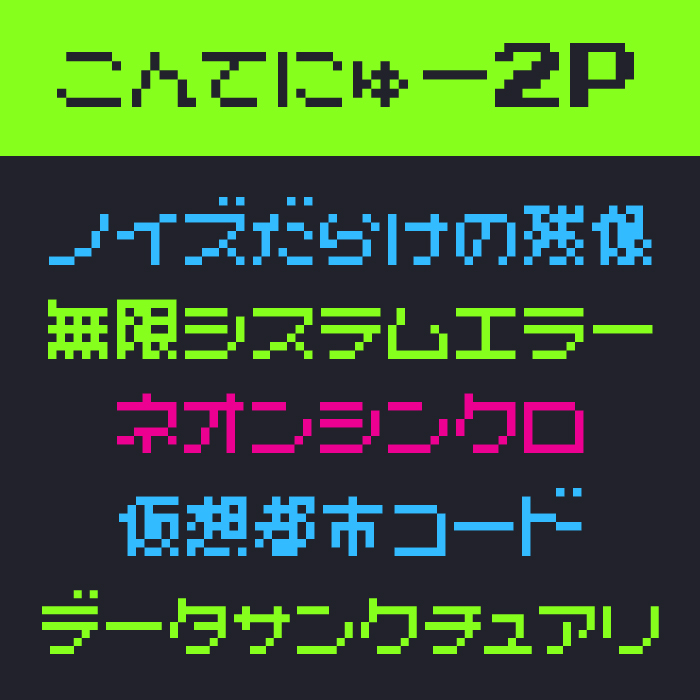
こんてにゅー 2Pフォントは、昔のゲーム画面を思わせるレトロでカクカクしたピクセル感が魅力のフォントです。デジタルノイズやエラーメッセージ風の表現にぴったりで、80〜90年代テイストのデザインにも相性抜群です。
瀞ノグリッチ明朝
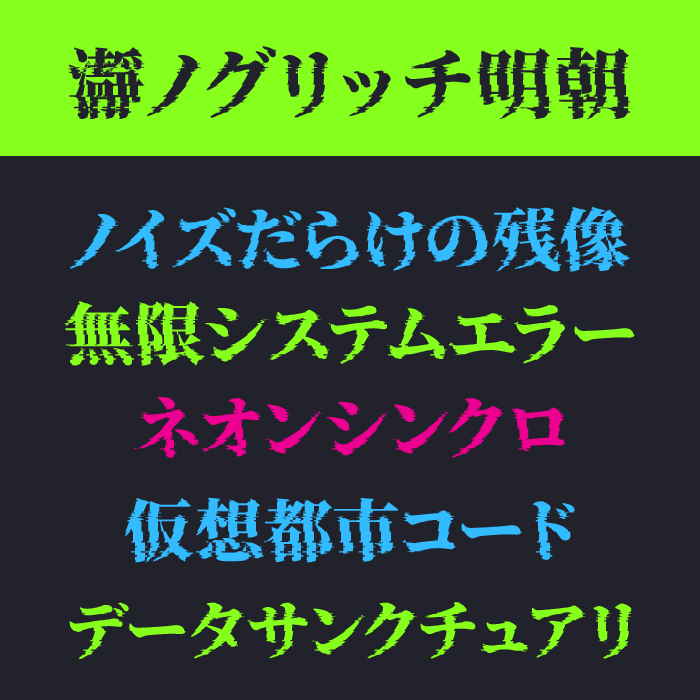
瀞ノグリッチ明朝フォントは、壊れかけた映像のようにザラついた輪郭が特徴の明朝体です。文字のひび割れやゆがみがグリッチ演出とマッチし、ホラー・SF・電脳世界系のタイトルロゴに使いたくなる雰囲気です。
ドット道玄坂12
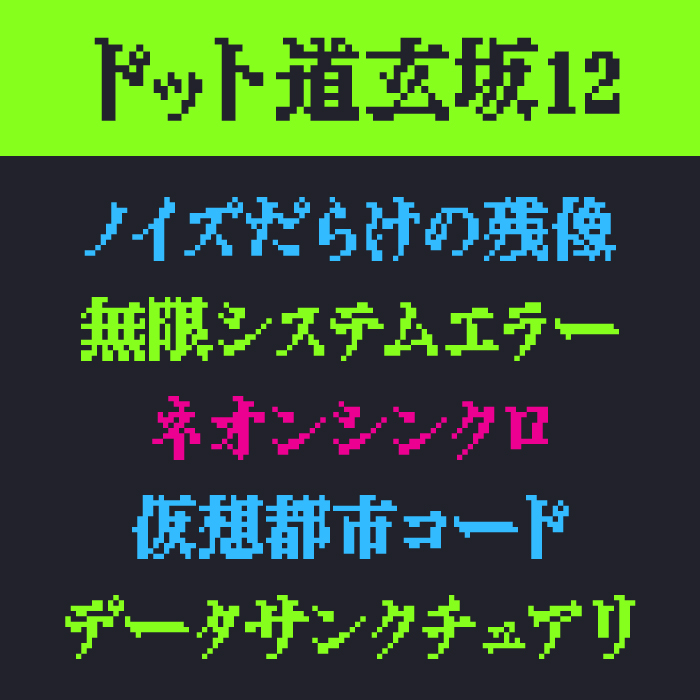
ドット道玄坂12フォントは、ドット感あふれる画素表現で構成されたレトロゲーム風のフォントです。太く安定感のある造形で、ビビッドなネオン配色と合わせることでY2Kやサイバーパンク的世界観がしっかり伝わります。
地方野球場電光掲示板
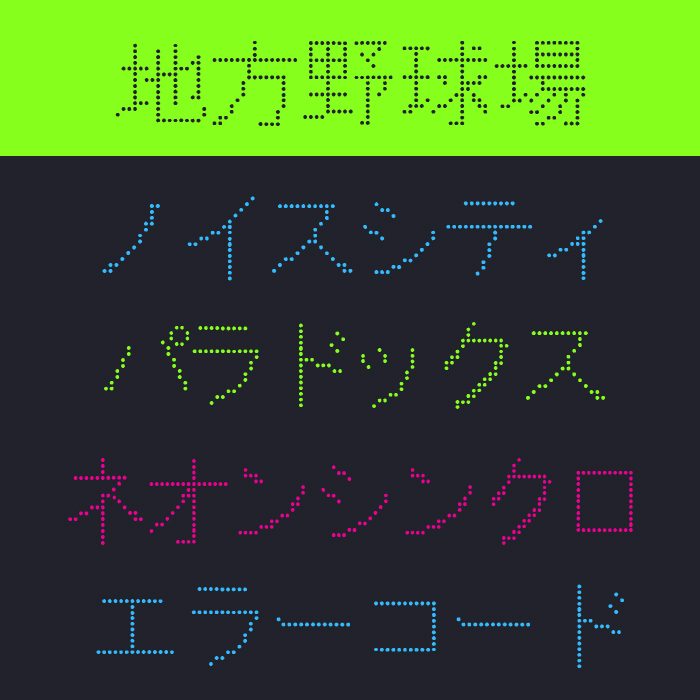
地方野球場フォントは、点線だけで構成されたユニークなディスプレイ書体です。スコアボードや電光掲示のような雰囲気をもち、情報表示やサイバー都市のビジュアル表現にぴったりな存在感を放ちます。
レシートフォント
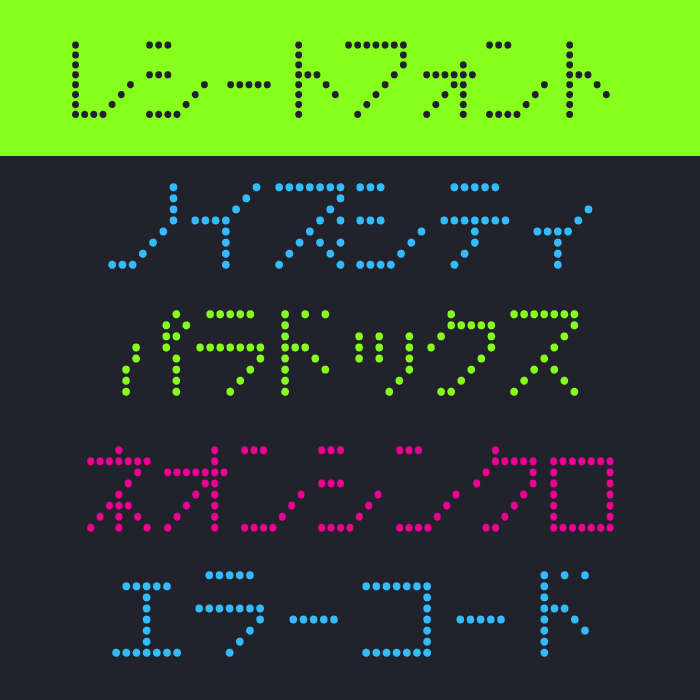
レシートフォントは、実在するレシート印字を模したような細かいドットによる構成がユニークです。古びたレジプリンタやエラー出力などの世界観にハマりやすく、廃墟テックやアンビエント系演出にもおすすめです。
オリエンタル
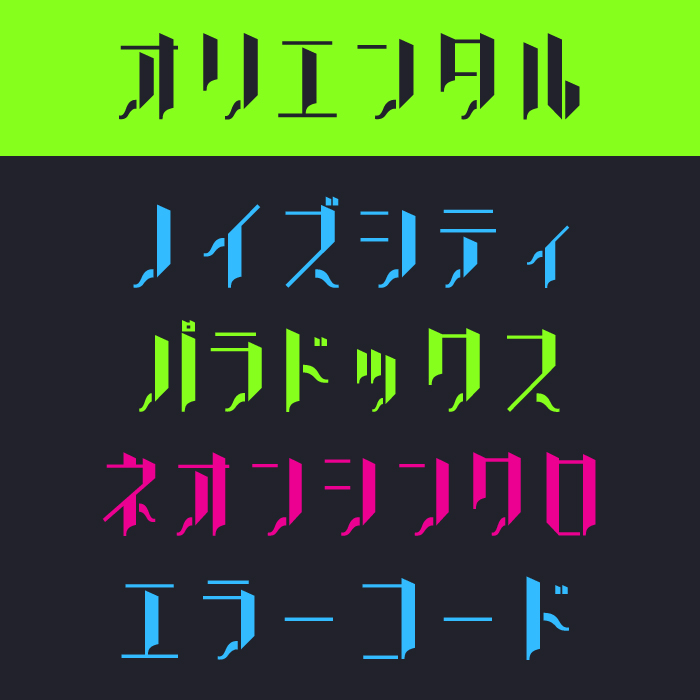
オリエンタルフォントは、漢字の一部が抜け落ちたようなデザインと、角度のあるパーツが特徴の装飾的フォントです。デジタル故障や監視社会、ブロークンな世界観を表現するタイトルやUIに適しています。
JikiTourai
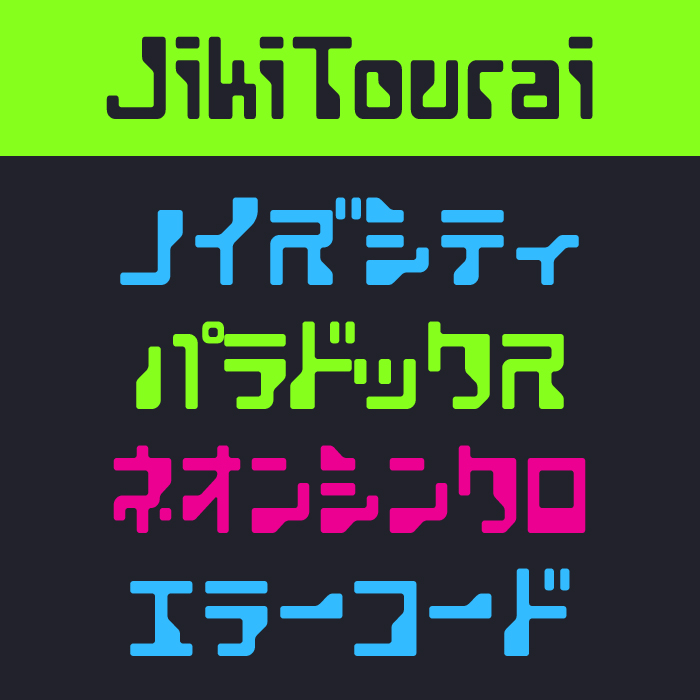
JikiTouraiフォントは、視認性を保ちながらもサイバーな断片感を備えた近未来感あふれるフォントです。電子基板やハッキング画面のような印象を与え、ゲームやSF演出にスピード感と鋭さを加えてくれます。
まるきや
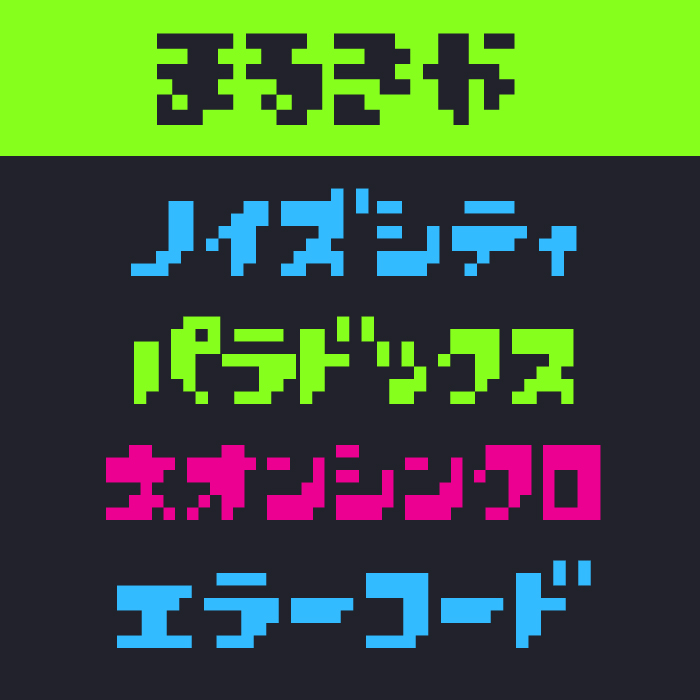
まるきやフォントは、ゲームボーイ風の粗いビット感と、ところどころのドット欠けが絶妙なデザインを生むピクセル書体です。ラフさの中に均整もあり、レトロフューチャーな演出に効果的に使えます。
ノンビット
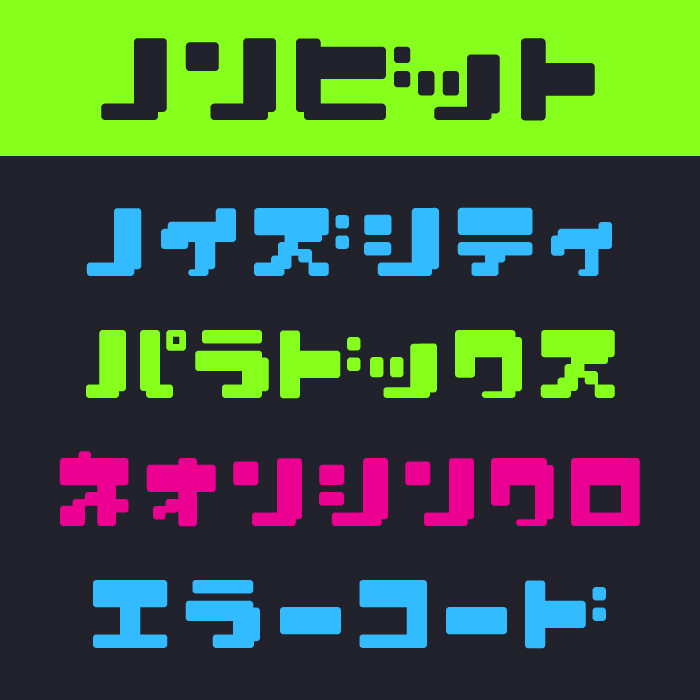
ノンビットフォントは、ビットの粒が組み合わさったようなカクカクとした親しみやすいフォルムのフォントです。かわいさとデジタルっぽさのバランスが絶妙で、子ども向けSF作品などにもおすすめです。
デジタルデゾレーションプラス
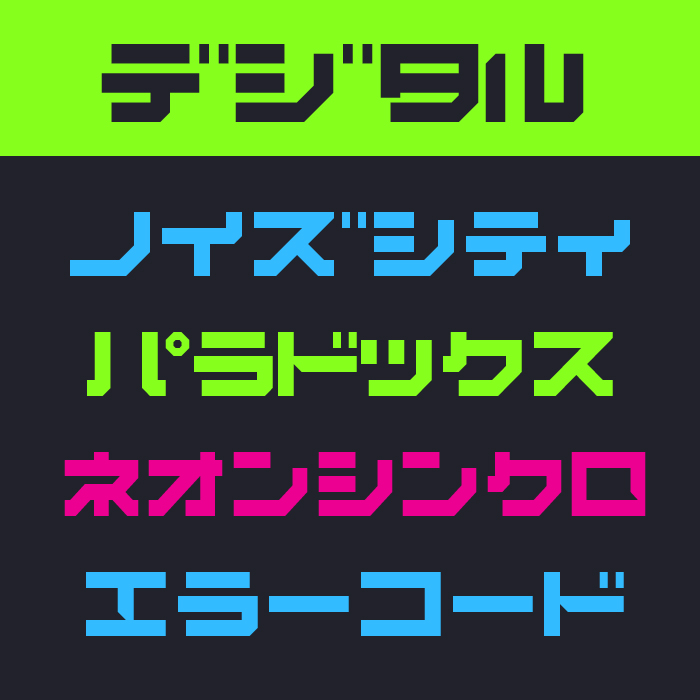
デジタルデゾレーションプラスフォントは、ジャギー感を活かした鋭角的なデザインで構成される文字が特徴です。ゲームUIやエラーメッセージ、機械的な印象を与えるシーンで映える、エッジの効いたデジタル風フォントです。
時をかける数字
時をかける数字フォントは、直線と分断されたパーツによってサイバーパンクな都市の喧騒を思わせる、攻めた雰囲気のフォントです。情報が錯綜する未来の街を思わせるようなビジュアルで、テクノロジーやエラー演出といったテーマにぴったりなフォントです。